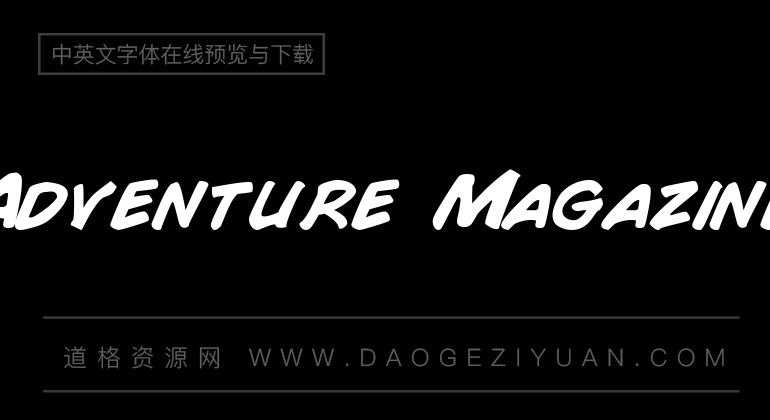
Adventure Magazine 字体是一种动态的、有趣的字体,它具有独特的曲线、节奏感和多层次的细节,使它适合用于多种冒险主题的文字排版。它的特点是它具有活力和张力,可以为文字提供强烈的视觉冲击力,增强文字的吸引力。它还具有良好的可读性,使文字更加清晰易读,有助于增强文字的可读性。内容介绍
Adventure Magazine是一款非常不错的手写艺术字体,具有很好的视觉感,适合于文化类的宣传设计、商业类品牌的广告和产品包装设计以及个性化文字排版等较多场景。